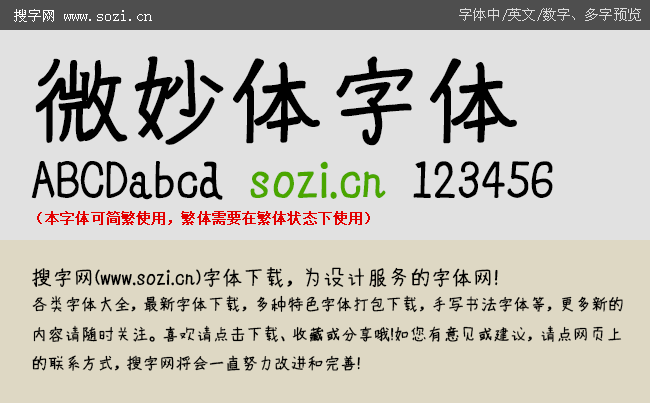
微妙體字體
搜字網(wǎng)給大家提供一款很萌的手寫(xiě)風(fēng)格手機(jī)中文字體下載。修改者給他起了個(gè)微妙體字體這么萌的名字,這款手機(jī)字體是是仿照小朋友的筆體制作的卡通手寫(xiě)字體。趣味性實(shí)足,該手機(jī)字體個(gè)性實(shí)足,趣味性強(qiáng),又保持了文字的識(shí)別度,特別適合喜歡手機(jī)字體個(gè)性一些的朋友在手機(jī)上安裝使用。